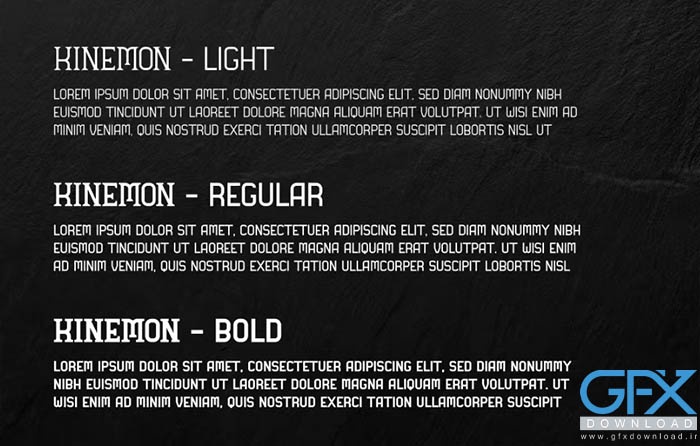
دانلود فونت نازک KINEMON
دانلود فونت نازک KINEMON به سبک نازک، مینیمالیستی و مدرن ارائه شده است. این فونت نمایشگر ظاهری تمیز دارد. در اشکال رسمی، مانند عنوان مجله، عنوان، روزنامه، عنوان فیلم، بروشور، پوستر، جلد کتاب، لوگو، بنر کاملا مناسب است.
فونت انگلیسی نازک KINEMON
همچنین می توان از این فونت انگلیسی در آثار هنری در مقیاس بزرگ استفاده کرد. KINEMON دارای نسخه های سبک، معمولی و پررنگ است. حروف بزرگ و کوچک هر دو به سبک بزرگ هستند.